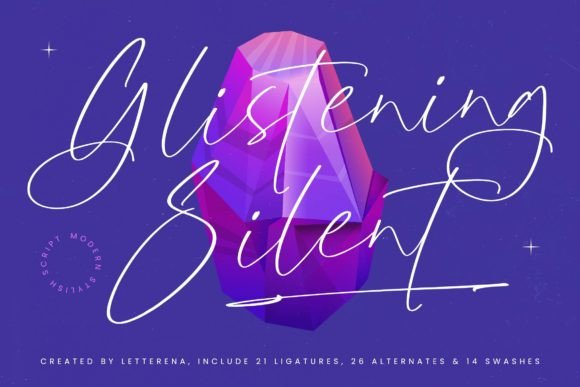
Glistening Silent
Encontrar los elementos de diseño adecuados puede ser un desafío, pero Glistening Silent ofrece una colección excepcional que eleva tu trabajo al instante.
Elaborado con precisión, Glistening Silent proporciona vectores limpios, tipografía suave y una licencia comercial para tu tranquilidad.